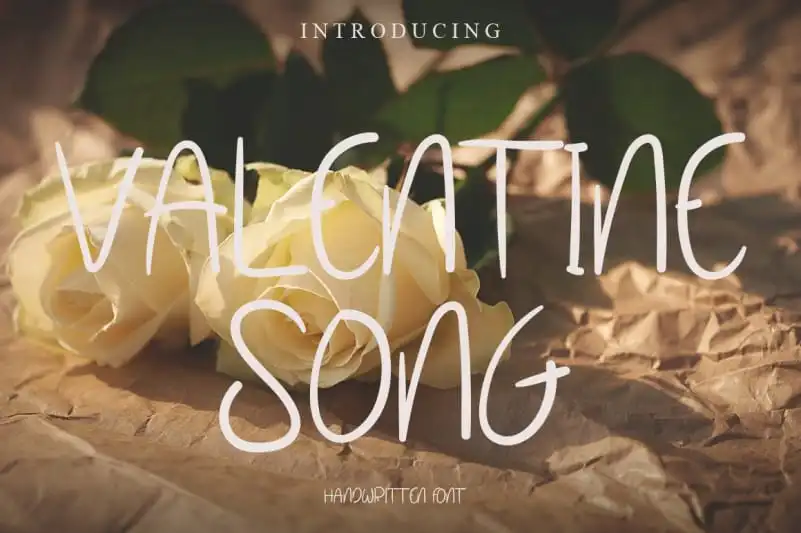
A Valentine Song Font é uma escolha perfeita para aqueles que buscam um toque autêntico em seus designs digitais. Desenvolvida pelo designer levincreative, essa fonte escrita a mão simples e relaxada se destaca por sua naturalidade e flexibilidade. Ela é adaptável a diversos tipos de projetos, seja para cartões personalizados ou gráficos digitais. O resultado? Seus trabalhos ganham um toque especial que os eleva a altitudes únicas e singelas. Com seu formato handwritten, a fonte Valentine Song traz uma atmosfera encantada para qualquer projeto de design, sem esforço algum. Ideal tanto para designers profissionais quanto para iniciantes apaixonados por gráficos, esta fonte é um tesouro inegável na categoria de Handwritten Fonts.